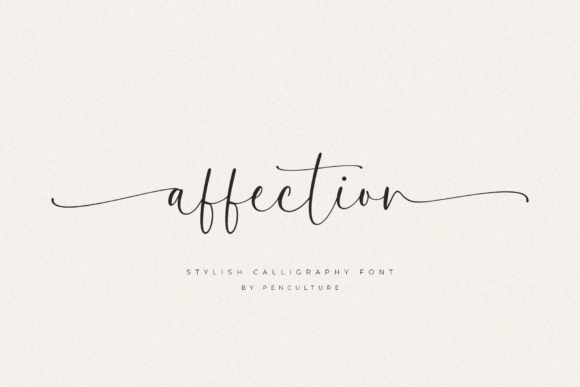
Affection
Affection : la police calligraphique qui séduit par son élégance décontractée
Si vous recherchez une typographie à la fois charmante et stylée, Affection répond parfaitement à vos attentes. Cette police calligraphique se distingue par ses swashes fluides et ses formes de lettres simples mais captivantes. Elle incarne un équilibre parfait entre raffinement et décontraction, idéal pour donner du caractère à tous vos projets créatifs.
Pourquoi choisir Affection ?
- Design versatile : ses courbes légères conviennent aussi bien aux invitations de mariage qu’aux cartes de vœux, en passant par le branding et les publications sur les réseaux sociaux.
- Lisibilité assurée : malgré ses ornements élégants, chaque caractère reste clair et lisible, même en petite taille.
- Impact visuel : le style « effortless swash » attire immédiatement le regard, renforçant l’identité visuelle de votre marque ou événement.
Applications idéales pour Affection
- Invitations de mariage : créez des cartons élégants qui reflètent la douceur et la romance.
- Branding & identité visuelle : donnez à votre logo ou à vos supports marketing une touche de sophistication décontractée.
- Cartes de vœux et papeterie : ajoutez une note personnelle et chaleureuse à chaque message.
- Contenus pour les réseaux sociaux : boostez l’engagement avec des citations ou des titres qui se démarquent.
- Supports imprimés divers (menus, flyers, affiches) : assurez une cohérence esthétique sur tous vos supports.
Conclusion
Affection n’est pas seulement une police de caractères ; c’est une véritable déclaration d’amour à la typographie. Sa capacité à mêler simplicité et élégance en fait le choix incontournable pour tous ceux qui souhaitent captiver l’attention tout en conservant une allure naturelle et raffinée. Intégrez dès maintenant Affection dans vos projets et laissez son charme irrésistible parler pour vous.